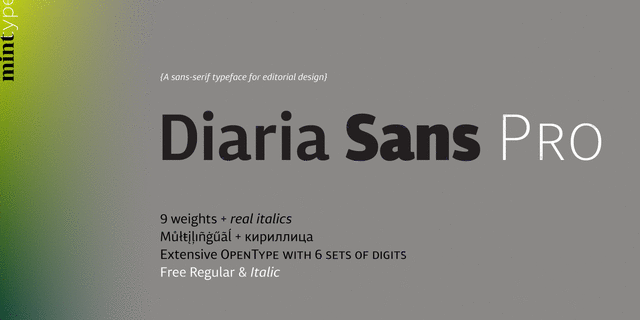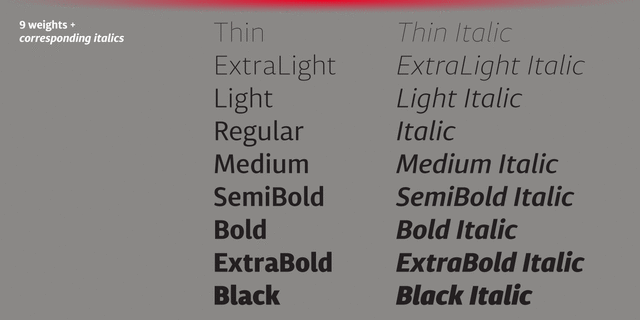
Diaria Sans Pro – это гротесковая версия шрифта Diaria Pro. Благодаря широкому набору из 9 насыщенностей, курсивных начертаний, расширенной языковой поддержке и различным OpenType-фичам, это шрифтовое семейство позволяет создавать визуальную иерархию в печатных и мультимедийных изданиях любой сложности.
Этот современный гротеск разработан как универсальная читабельная «рабочая лошадка» для текстов и заголовков. Достаточно высокие строчные знаки и статичные формы способствуют комфортному чтению, как узких газетных колонок, так и страниц электронных изданий.
Шрифт разработал и выпустил Андрей Константинов в студии Mint Type в 2016 году.